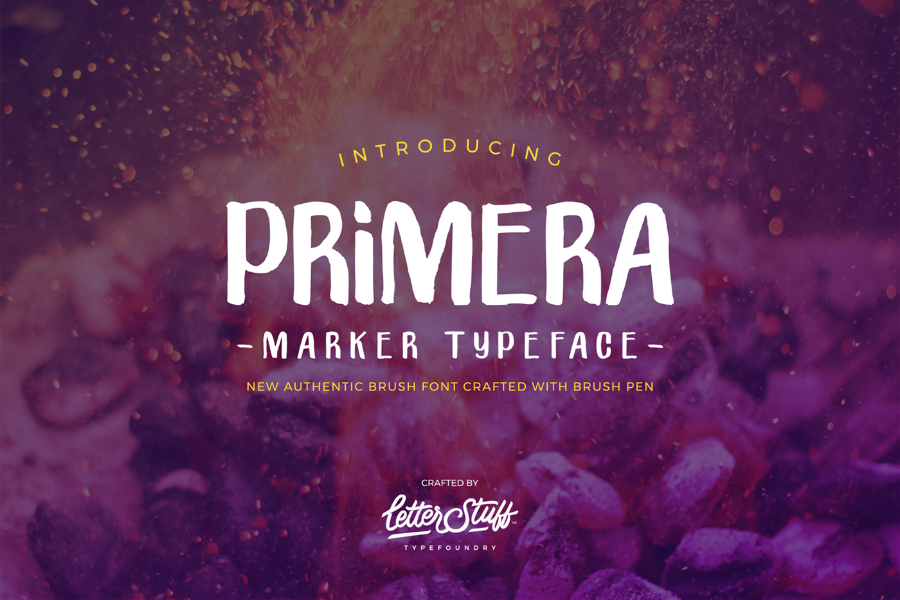
Primera Typeface
A Primera Typeface é uma fonte script que transmite elegância e versatilidade ao texto. Ela foi criada pelo Designer Hamilton com a ajuda do LetterStuff™ Typefoundry, oferecendo um estilo autêntico e moderno. Esta fonte se destaca para aplicações de destaque, desde logotipos até postagens em redes sociais como o Instagram. Suas linhas fluidas permitem que você crie elementos visuais memoráveis para suas camisetas personalizadas, selos ou capas de livros, dando um toque criativo e sofisticado a seus projetos. Seja para criar uma identidade visual única ou adicionar um toque pessoal em seu design, a Primera Typeface tem tudo o que você precisa.